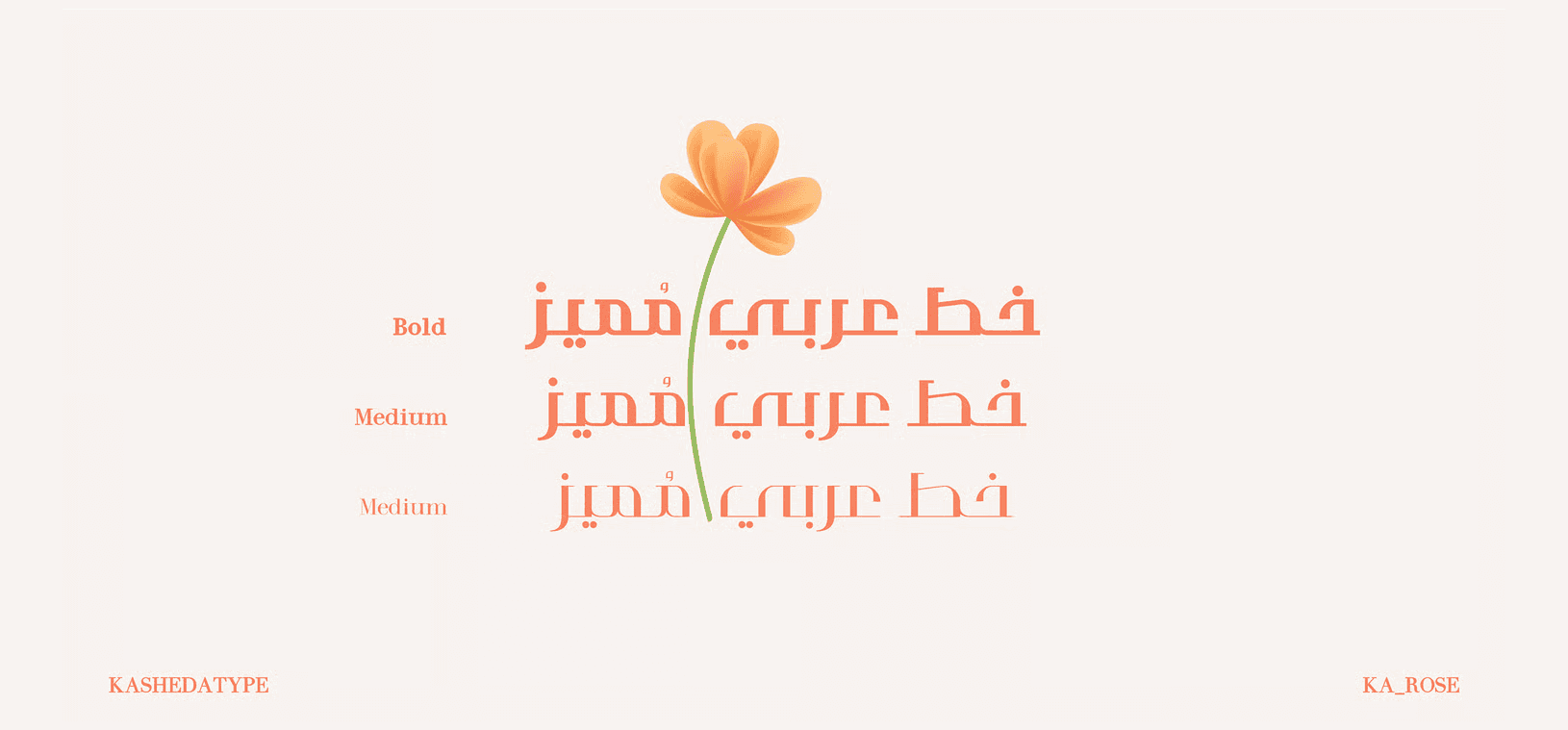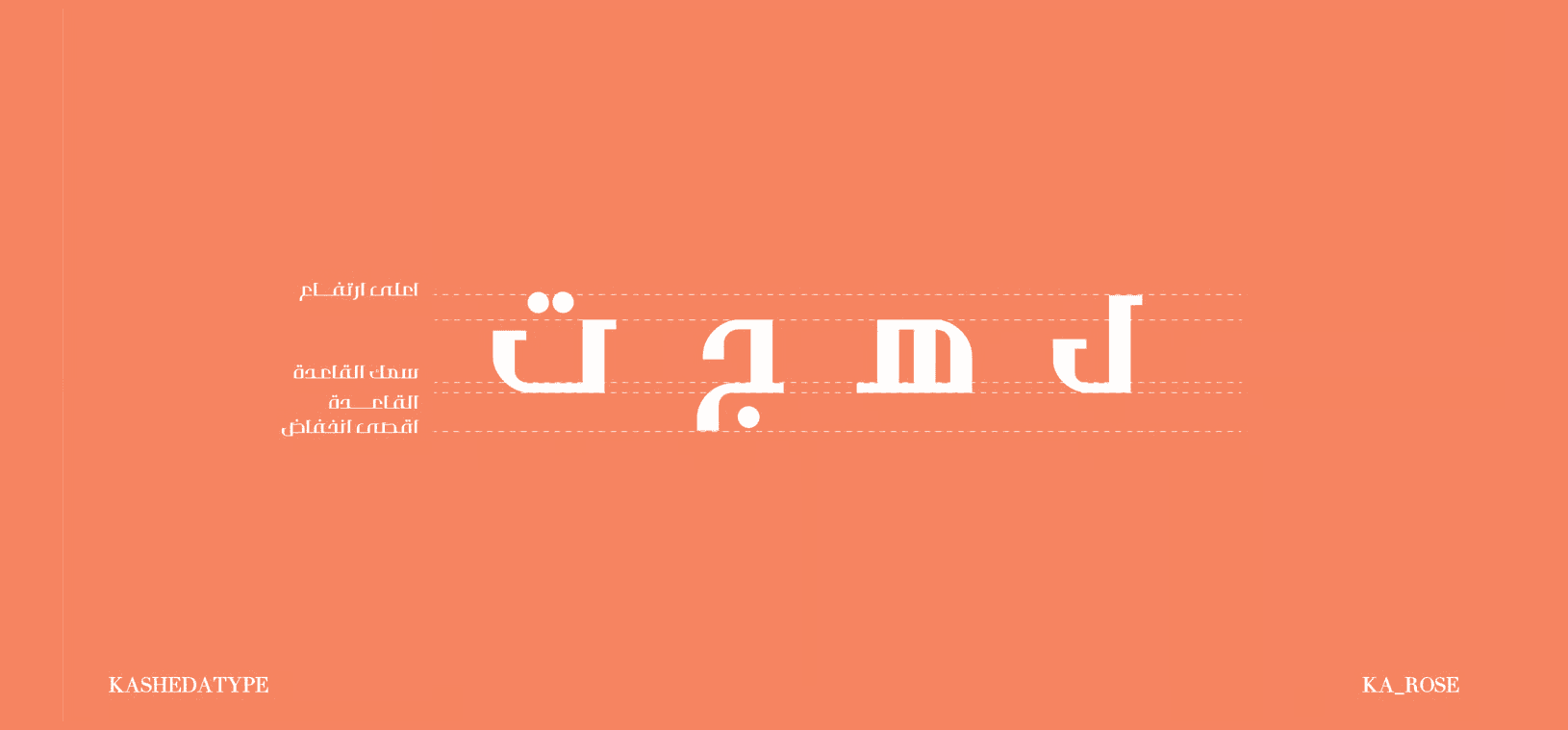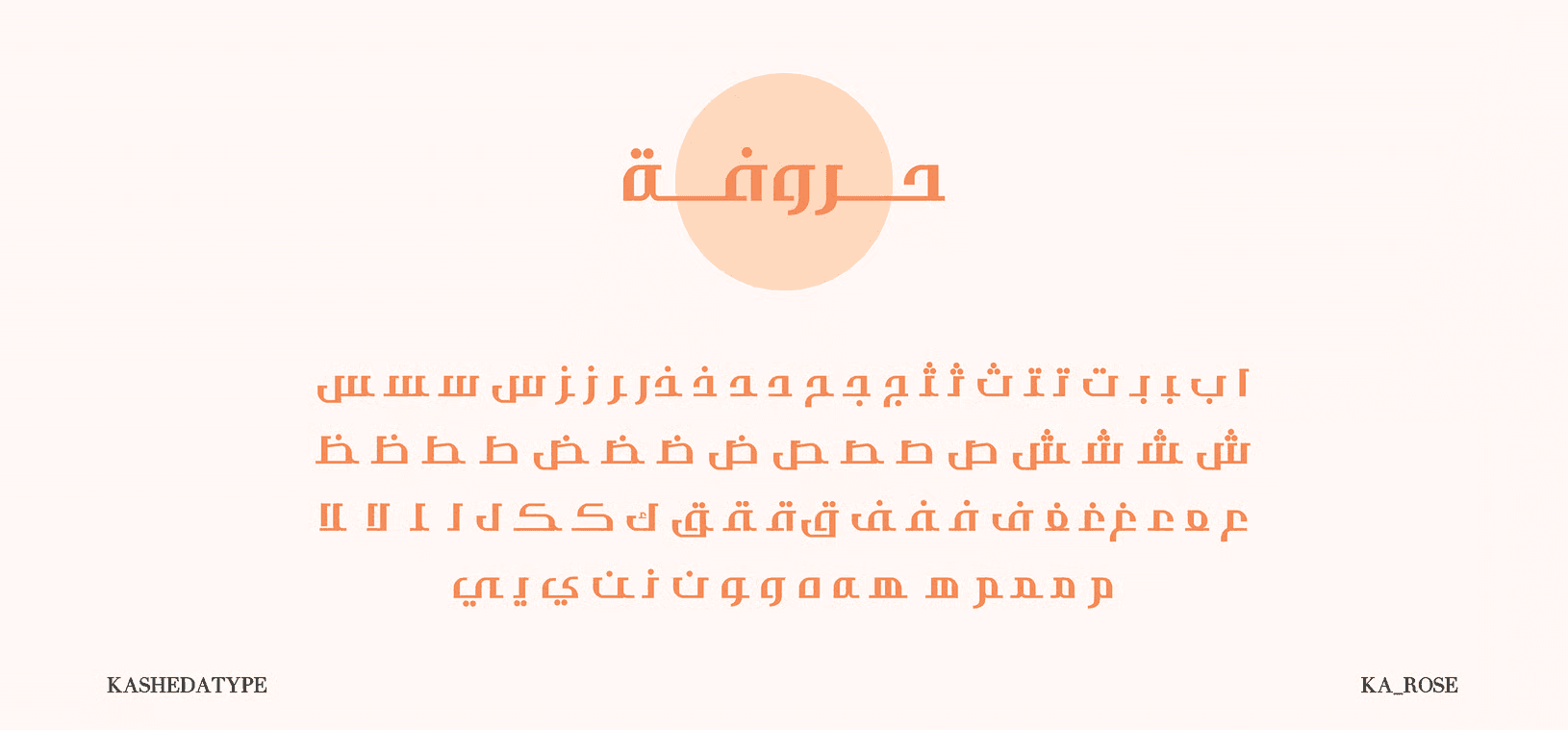
يتميز خط روز بأسلوب أنثوي رقيق مستوحى من بساطة الزهور وانسيابيتها. يأتي بثلاثة أوزان تتيح تنوعًا في الاستخدام، ويعد مثاليًا لتصاميم الهوية، الدعوات، التغليف، والمطبوعات التي تتطلب مظهرًا هادئًا وجذابًا. يجمع الخط بين التوازن الجمالي وسهولة القراءة، مما يجعله خيارًا مثاليًا للمشاريع ذات الطابع الرومانسي أو الفني.